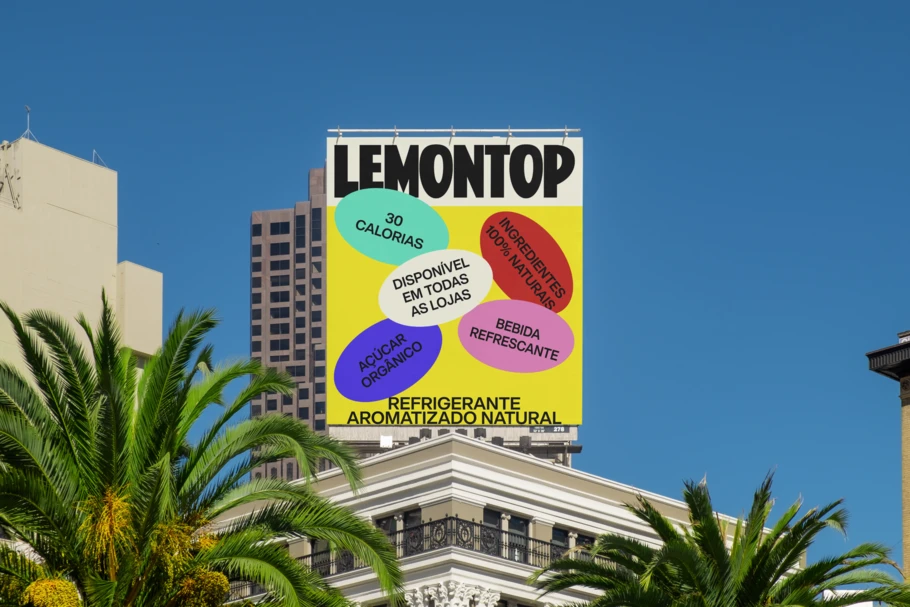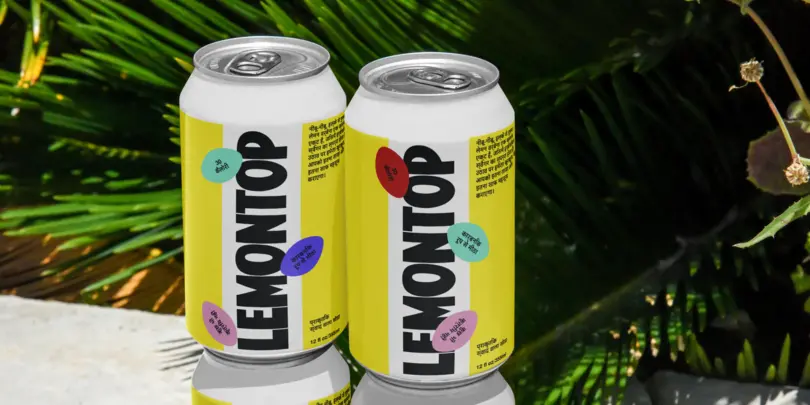
Seu guia para uma marca consistente, poderosa e significativa.
Nas palavras do Diretor Criativo da Monotype, Charles Nix: “A marca está sempre em evolução. Não existem marcas estáticas”. E como as marcas estão constantemente evoluindo, elas precisam de pilares para mantê-las unidas.
A tipografia é um desses pilares. E ainda que seja papel dos designers a se ocuparem da altura de “x” e a forma do “g” em um tipo específico, todos na organização têm a responsabilidade de prezar pela consistência de marca.
A consistência não é um coadjuvante: ela é um elemento central.
Sabemos que as marcas são poderosas. Elas criam confiança, estabelecem identidade, constroem um espírito sólido e garantem a fidelidade dos clientes. A aplicação consistente da tipografia mantém todos alinhados e apontando para a mesma direção. Definir e manter uma tipografia consistente expressa o seguinte: “Os valores da nossa marca são importantes. Nós acreditamos neles. Nós os vivemos. A maneira como nos comunicamos uns com os outros verbal e visualmente é um reflexo importante disso”.
Para que seu cliente saiba quem você é – e para confiar em você, criar relacionamentos com você, fazer negócios com você e ajudar você a ter sucesso –, sua marca precisa conhecer a si mesma e transmitir essa identidade a cada passo. Uma tipografia consistente e eficaz não é um luxo, como o camarote em um estádio. Ela é o próprio estádio. É uma premissa básica do negócio. É uma necessidade empresarial.
Como definir e manter a consistência.
Pode ser difícil prever a jornada que uma marca percorrerá ao longo dos anos. Pense nas marcas que existiam antes da Internet e dos aplicativos, sem mencionar que as fontes baseadas na Web ainda nem existiam. Marcas da geração Web 2.0 terão que se adaptar à medida que o mundo muda para a Web3, para o metaverso e o que vier depois disso. Dito isso, quais são os passos práticos que uma organização pode dar para garantir a consistência de marca e de sua tipografia? Vamos analisar.
Acompanhe as fontes de texto e exibição.
Esteja você desenvolvendo brindes, um papel timbrado ou uma apresentação interna, conheça as fontes primárias e secundárias da marca desde o início. Embora não haja um número mínimo de fontes que uma marca possa escolher, e usar apenas uma exigiria um alto nível de disciplina, é importante ter ao menos as fontes de texto e possivelmente as fontes display definidas. Além disso, você pode precisar recorrer à gaveta do seu designer para pegar um pouco de “tempero”, ou seja, uma nova fonte display para uma ocasião especial. Ter uma maneira universal de saber o que se aplica a cada situação é essencial para o sucesso e consistência da marca.
Preserve a simplicidade, com ou sem serifa.
Considere isso uma regra para qualquer coisa em branding, além da hierarquia da tipografia: se o sistema for tão complexo a ponto de nem mesmo os criadores conseguirem manter a ordem, então não há esperança para os demais parceiros e usuários da marca. Com a Monotype Fonts como plataforma de gerenciamento, os administradores podem ter uma visão geral das fontes da organização e permitir acesso apenas às fontes que os funcionários devem usar.
Deixe todo mundo alinhado.
O tom de voz de uma marca é expresso através da tipografia. Todo mundo precisa entender isso e estar de acordo, esteja ou não diretamente envolvido com o design da marca. Isso ajuda a ter uma plataforma ou sistema que integre facilmente as fontes da marca em um programa de design. Com a Monotype Fonts, basta apertar o botão “sincronizar”. Mas, em um nível mais elevado, entender desde o “porquê” da marca até a escolha da fonte é um fator interno, se não psicológico, que preserva a solidez da marca.
Realize auditorias de marca constantes.
A marca está sempre em evolução. Realizar auditorias ou avaliações constantes da marca internamente, ou a ajuda de parceiros externos, é sempre uma boa ideia. Uma avaliação deve adotar uma visão geral de alto nível e minuciosa. A consistência, o tom de voz da marca, a relevância de redimensionamento, o contraste de cores, a legibilidade e muitos outros fatores devem ser considerados. O serviço de avaliação de fontes para marca da Monotype pode oferecer essas percepções, mantendo todos os aspectos alinhados e identificando quaisquer problemas no sistema.
Acima de tudo, comunique-se.
Os valores, o nome, o logotipo, a missão e outros elementos sustentam o que uma marca é, mesmo que ela esteja mudando; e a tipografia é a maneira como tudo isso é expresso. Se houver uma mudança, informe a todos. Se houver um problema de acesso, resolva-o. Se estiver usando a Monotype Fonts, por exemplo, todos na equipe de design e digital devem ter o acesso necessário.
Por que a Monotype Fonts?
Ao procurar uma família de fontes que atenda a todas as necessidades da sua marca, é vantajoso ter uma ferramenta de pesquisa de primeira linha, como a que se encontra integrada à Monotype Fonts. Encontre e filtre fontes por estilo, humor, idioma, características da fonte, formato da fonte, fundidora e muito mais.
Além de mais de 400 mil opções de fontes, a Monotype Fonts facilita a sincronização e o compartilhamento de arquivos de fonte com outros. Além disso, ela oferece upload fácil de fontes de terceiros, um contrato de licença, sincronização simplificada, bibliotecas organizadas e controle de acesso – um grande redutor de erros.
Por exemplo, se você tem uma equipe em sua organização (ou fora dela) que precisa usar uma fonte específica ou um conjunto de fontes, pode restringir o acesso aos tipos e garantir que usem apenas as fontes correspondentes às diretrizes da marca. Nada de usar a “Helvetica” errada, mesmo achando que era a correta. E com relação a isso, a Monotype Fonts é tudo de que você precisa. Para saber mais sobre como a Monotype Fonts pode elevar o gerenciamento de fontes da sua organização e ajudar a construir marcas consistentes, visite MonotypeFonts.com.